黑体字是现代汉字体系中最重要的字体之一。尤其是电脑和互联网的广泛普及后,黑体字的价值得到巨大的展现。黑体字是一种字面呈现为正方形的粗壮字体,字形端庄,笔画横平竖直,结构醒目严密,因而广泛应用在各种设计中。例如下面 字体图片,就是十足展现了黑体的特征。
这张图片上有着黑体字特点的字体就是“汉标手写巨黑”。设计师在艺术创作时用粗毛笔大胆书写,笔画清朗有劲儿,简约美观。在黑体的基础上融入了中国书法的气韵,奕奕有神。充满张力的曲线加上精准的集合线条结构。这款字体稳重的风格非常适用于信息排印、屏幕显示、ppt标题等。
这款“汉标外线黑体”在黑字形的外部增加了细线,简练的正方笔形,笔画粗壮有力、撇捺不尖锐,有种立体的视觉感受。笔画穿插又避让,精准细致,整齐美观又大方。使用在印刷、屏幕显示、logo设计等都是绝佳选择。
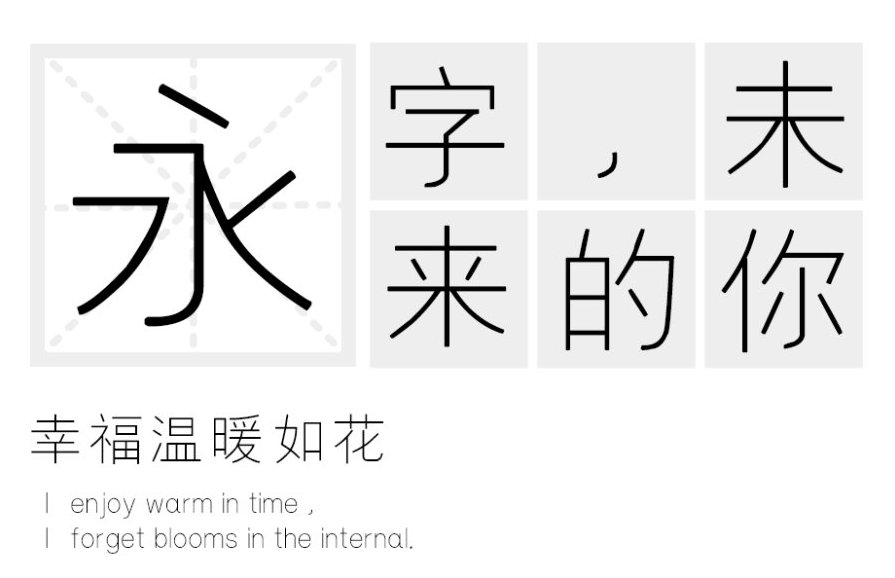
这款“汉标细黑体” ,在正统黑体上做了一些修改,字形保留了方正,但是减少了黑体的厚重感,汉标细黑体风格简静优雅,设计追求远距离读取的功能,笔画清晰便于 识别字体 。适用于标题和正文排版,尤其适合应用在空间导视、包装设计、广告等领域。